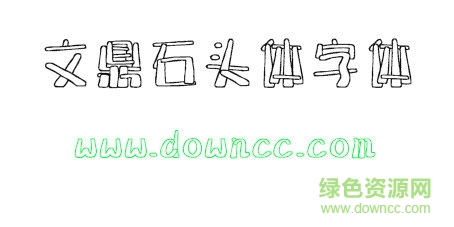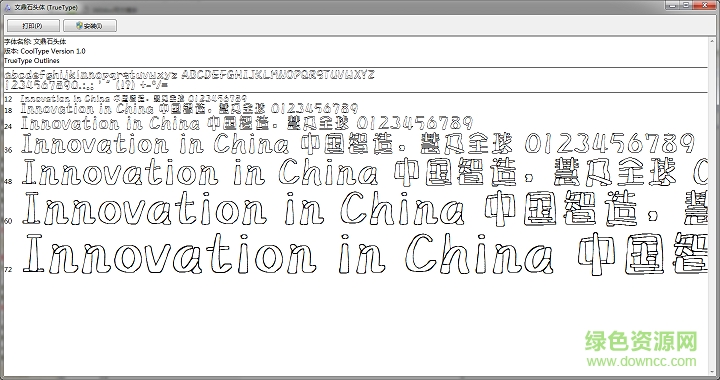
文鼎石頭體是文鼎字體庫中少有的空心字體。該字體給人的感覺像畫出來的一樣,特色鮮明,適用于藝術(shù)創(chuàng)作中使用。喜歡該類字體的朋友就趕緊來綠色資源網(wǎng)下載使用吧!
文鼎石頭體是款應(yīng)用于廣告設(shè)計方面的中文簡體漢字,該字體以石頭為原形而設(shè)計,端正大方得體,一筆一畫非常藝術(shù),整體效果非常出色,可以適用于名片設(shè)計、平面設(shè)計、廣告設(shè)計、報紙雜志等領(lǐng)域,讓你擁有更加富有個性的字體設(shè)計。